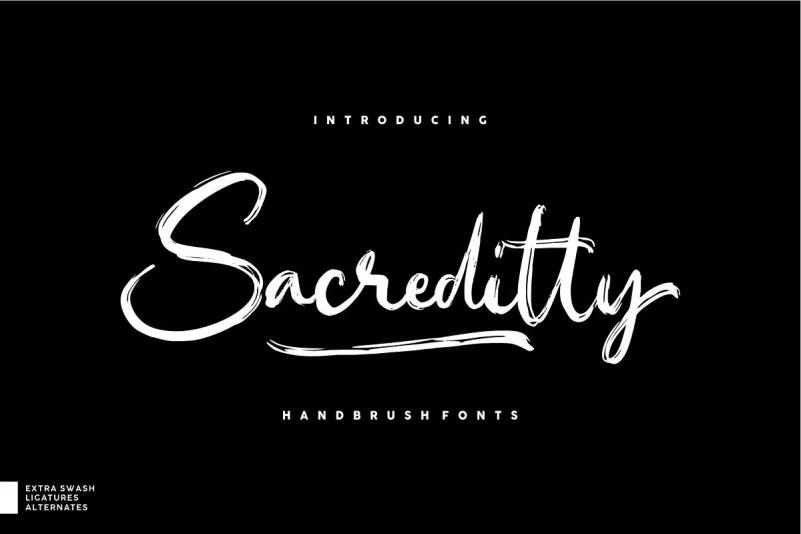
Sacreditty Handbrush Font – Download Grátis
Esta é uma fonte de script criada com a técnica do desenho à mão e pintura de canetinhas secas. Ela apresenta traços arredondados elegantes que se unem a um toque urbano fresco, oferecendo um estilo de escrita sofisticado que certamente adicionará uma aparição atrativa aos seus designs de logotipo, imagens da marca, citações escritas à mão, embalagens, produtos e posts nas redes sociais. Zziplex é o designer dessa fonte Sacreditty Handbrush, que completa a linha de fontes Garisman Std. Essa fonte é perfeita para quem busca um toque pessoal ou casual em seus projetos gráficos.